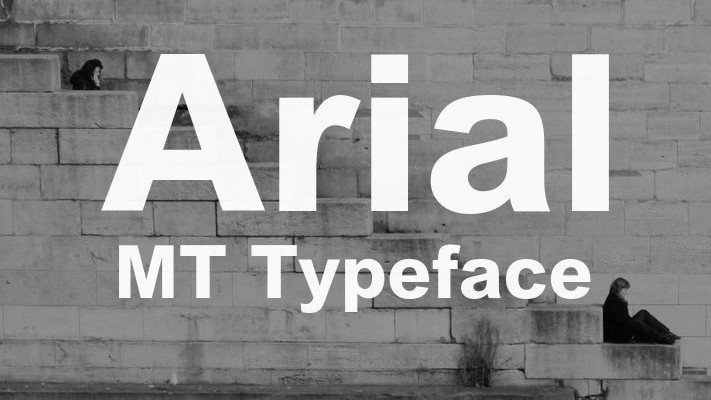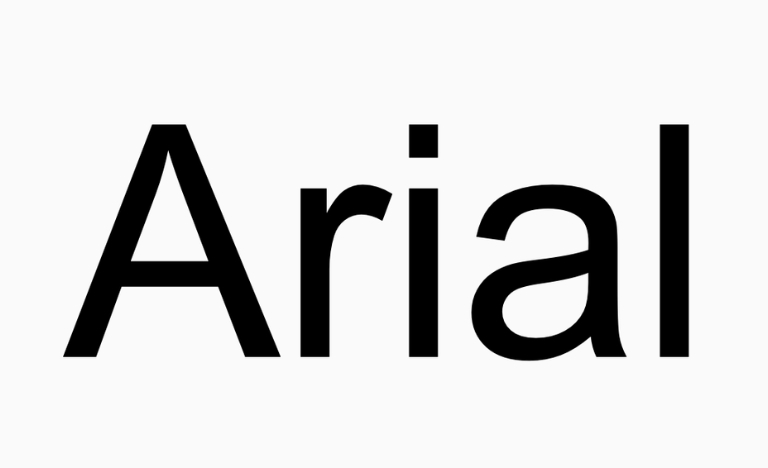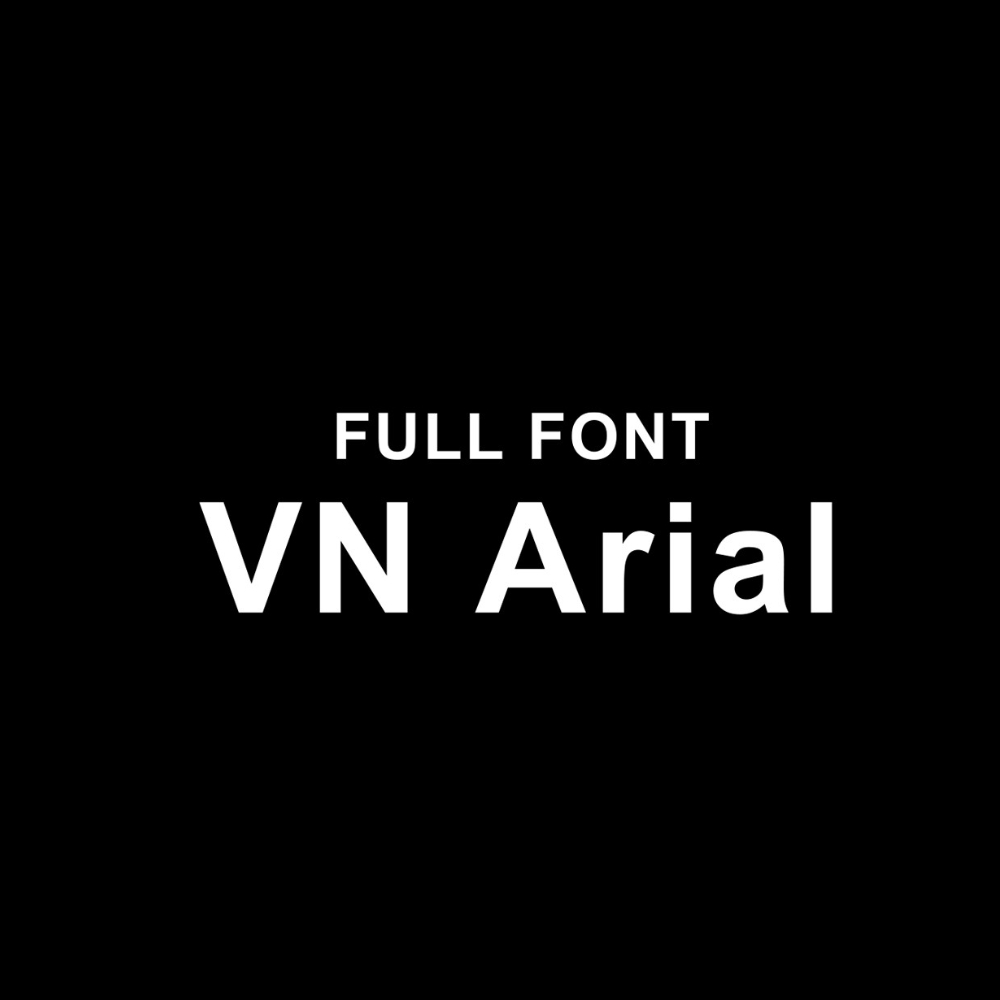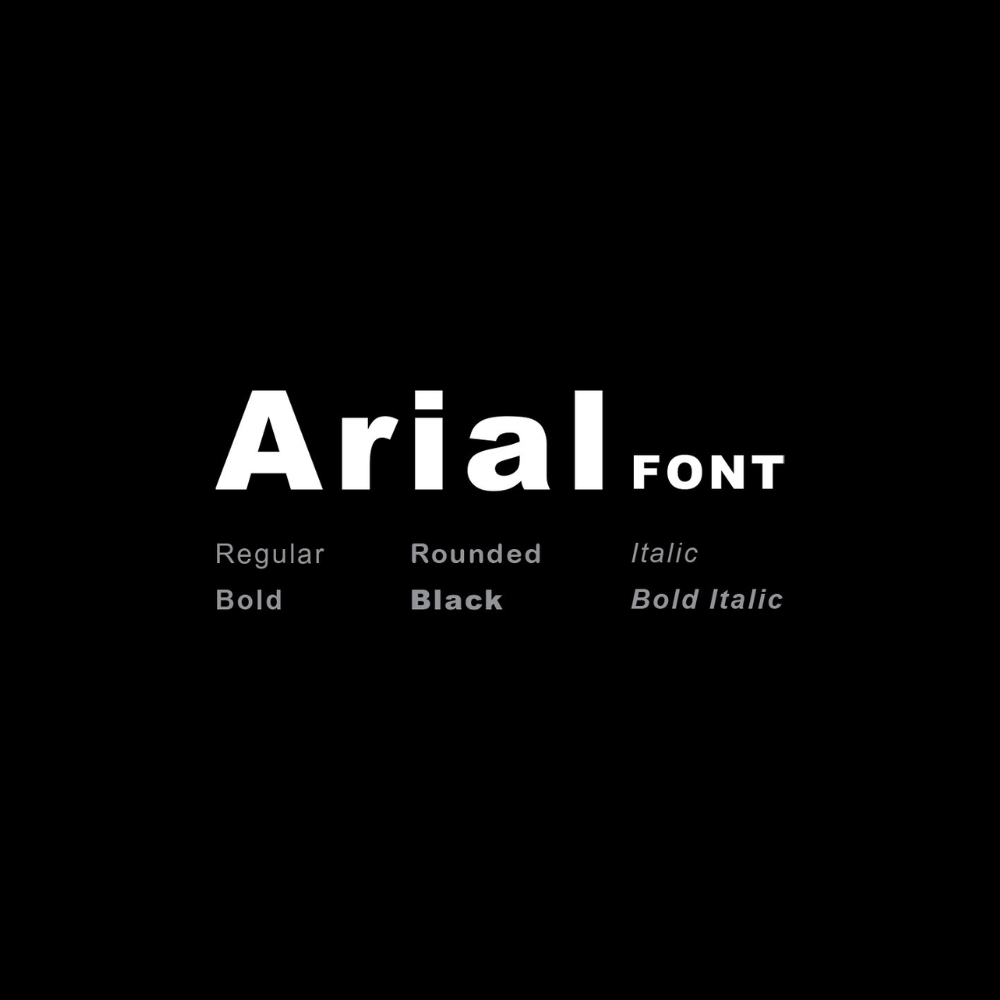
Arial là bộ phông chữ Sans-serif phổ biến trên toàn cầu nhờ độ rõ nét và tính trung tính vượt trội. Việc sở hữu đầy đủ bộ Arial download font giúp kiến trúc sư và kỹ sư trình bày hồ sơ kỹ thuật, bản vẽ CAD hay dự toán công trình một cách khoa học.
Đặc điểm nổi bật của phông chữ Arial trong trình bày hồ sơ chuyên ngành
Điểm đặc trưng của Arial chính là cấu trúc hình học đơn giản, các nét chữ có độ dày đồng nhất và loại bỏ hoàn toàn các chi tiết trang trí rườm rà. Thiết kế trung tính này giúp mắt người đọc dễ dàng nhận diện thông tin ngay cả ở kích thước rất nhỏ hoặc trong các điều kiện ánh sáng kém tại công trường. Download font Arial trọn bộ còn mang lại sự ổn định tuyệt vời khi chuyển đổi file giữa các máy tính khác nhau, vì đây là phông chữ hệ thống chuẩn mực trên hầu hết các nền tảng Windows và macOS.
Bên cạnh tính phổ biến, Arial sở hữu khả năng hiển thị rõ nét trên nhiều bề mặt vật liệu khác nhau. Dù được in trên bạt hiflex, khắc trên tấm panel cách nhiệt hay hiển thị trên màn hình smartphone, các cạnh chữ vẫn giữ được độ sắc sảo, không bị nhòe mờ. Đặc điểm này cực kỳ hữu ích cho những dự án yêu cầu thông tin kỹ thuật phải được truyền tải một cách nhanh chóng và chính xác đến đội ngũ thi công nhà lắp ghép và chủ đầu tư.
| Biến thể phông chữ | Đặc điểm thiết kế | Mục đích sử dụng |
|---|---|---|
| Arial Regular / Bold | Nét chữ tiêu chuẩn, cân đối, độ dày linh hoạt | Soạn thảo văn bản, tiêu đề báo cáo |
| Arial Narrow | Cấu trúc chữ hẹp, tiết kiệm diện tích ngang | Bảng tính dự toán, ghi chú bản vẽ hẹp |
| Arial Unicode MS | Hỗ trợ dải ký tự cực lớn, đa ngôn ngữ | Bản vẽ đa quốc gia, ký hiệu đặc biệt |
| Arial Black | Nét cực dày, tạo độ nhấn thị giác mạnh | Biển cảnh báo công trường, tiêu đề lớn |
Tư vấn lựa chọn: Bạn nên thực hiện Arial narrow download font khi cần trình bày các bảng khối lượng vật liệu dài trong Excel để dữ liệu không bị tràn trang. Trong khi đó, việc download font Arial unicode ms là phương án cần thiết cho các dự án có sử dụng ký hiệu kỹ thuật phức tạp hoặc cần hiển thị nhiều ngôn ngữ trên cùng một bản vẽ.
03 Ứng dụng font Arial hiệu quả trong công tác xây dựng
Nhờ vẻ ngoài khoa học và sự rõ ràng, bộ phông chữ này mang lại giá trị thực tế cao trong quá trình vận hành dự án kiến trúc và thi công:
- Ghi chú chi tiết trên bản vẽ AutoCAD: Sử dụng tải font Arial narrow cho các ghi chú kích thước giúp bản vẽ trông thông thoáng hơn. Điều này đặc biệt quan trọng trong các bản vẽ chi tiết lắp ghép nhà container hoặc nhà phố có mật độ thông tin dày đặc.
- Hệ thống biển báo và chỉ dẫn an toàn: Với đặc tính dễ đọc từ xa, Arial bold download font là lựa chọn tốt cho các biển chỉ dẫn hướng đi hoặc bảng nội quy tại công trường thi công nhà lắp ghép, giúp công nhân dễ dàng nắm bắt thông tin an toàn.
- Lập hồ sơ dự toán và quyết toán công trình: Arial giúp các con số trong bảng tính trở nên tách bạch, hạn chế tối đa nhầm lẫn số liệu khi làm việc với đơn vị kiểm toán hoặc chủ đầu tư.
03 Lưu ý bố cục để bản vẽ kiến trúc sử dụng font Arial chuyên nghiệp
Để khai thác hiệu quả vẻ đẹp trung tính của dòng font Sans-serif này mà không gây cảm giác đơn điệu, người thiết kế nên lưu tâm một số lưu ý kỹ thuật sau:
- Phân cấp thông tin bằng độ đậm: Hãy kết hợp Arial bold download font cho các tiêu đề chương trong hồ sơ năng lực và dùng Arial Regular cho nội dung chi tiết. Sự tương phản rõ rệt về độ dày sẽ giúp bố cục văn bản có chiều sâu và dễ theo dõi hơn.
- Kiểm soát khoảng cách dòng (Leading): Với các đoạn văn bản dài, bạn nên thiết lập khoảng cách dòng từ 1.2 đến 1.5 lần cỡ chữ để đảm bảo sự thông thoáng, giúp người đọc không bị mỏi mắt khi tiếp nhận các thuyết minh dự án dài.
- Đồng bộ phông chữ trong toàn bộ hồ sơ: Tránh việc sử dụng quá nhiều kiểu chữ khác nhau. Việc duy trì Arial xuyên suốt từ bản vẽ CAD đến báo cáo Word và slide Powerpoint giúp thương hiệu của bạn trông nhất quán và chuyên nghiệp.